- 산돌문화재단 주최 ‘2025 산돌 사이시옷’, 폰트 산업과 K-컬처의 접점을 탐구하며 성황리 개최
- 폰트 및 그래픽 디자이너, 엔지니어, 기획자, 예비 창업자, 관련 전공 학생 등 약 300여명 참석
- 한글 폰트를 매개로 문화,산업,대중을 연결하며 K-콘텐츠 생태계 확장 가능성 확인
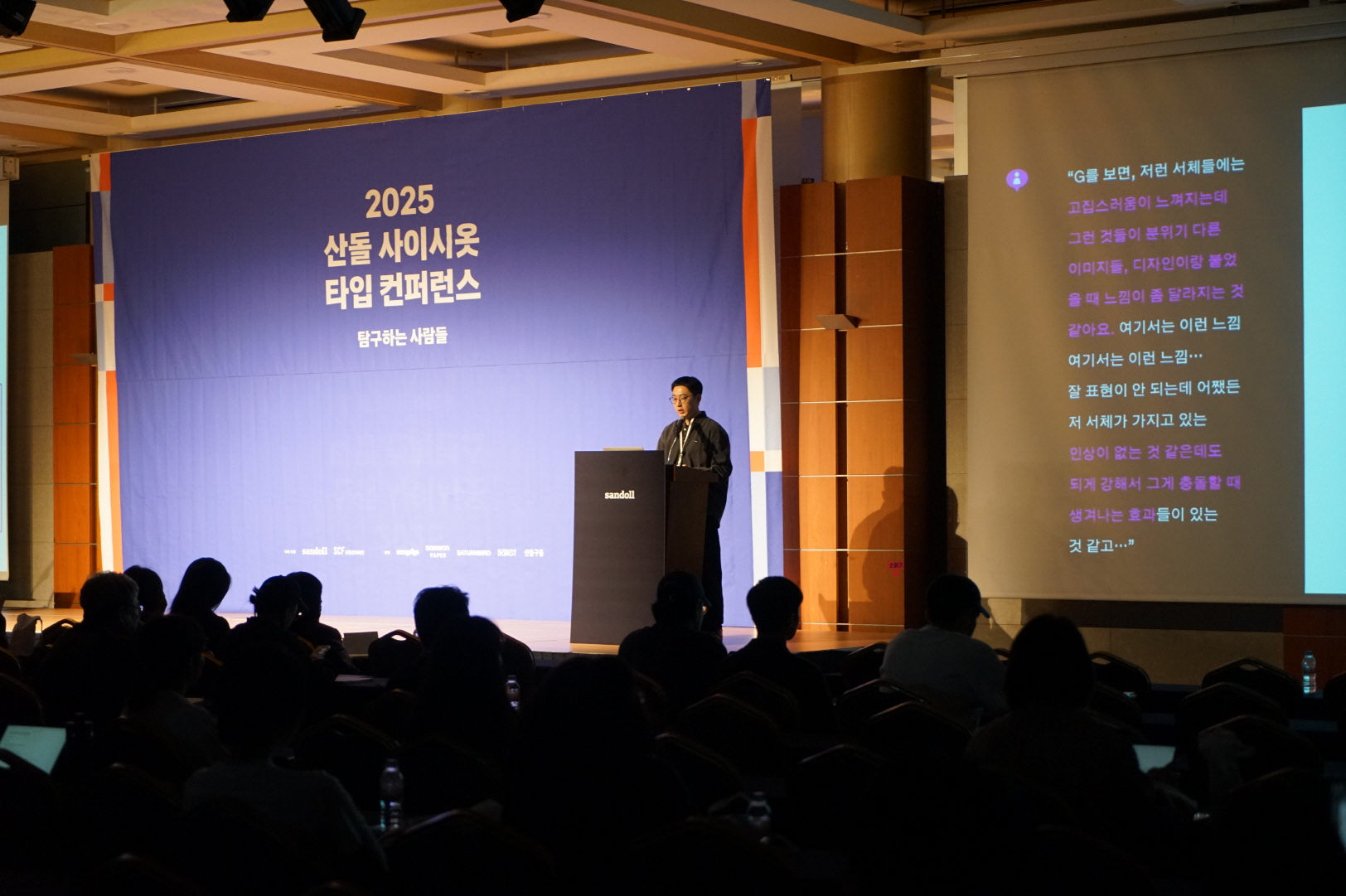
백범김구기념관 컨벤션홀에서 진행된 2025 산돌 사이시옷에 많은 청중이 모여 강연을 듣고 있다.
한글의 가치로 문화를 확산하는 재단법인 산돌문화재단(이사장 손연홍)이 주최하고 ㈜산돌(대표이사 윤영호)이 주관한 연례 폰트 컨퍼런스 ‘2025 산돌 사이시옷’이 지난 18일(토) 백범김구기념관 컨벤션홀에서 성황리에 막을 내렸다.
올해 사이시옷은 ‘탐구하는 사람들’을 주제로 열렸으며, 폰트 및 그래픽 디자이너, 엔지니어, 기획자, 예비 창업자, 관련 전공 학생 등 약 300여명이 참석해 폰트와 콘텐츠 산업의 현재와 미래를 함께 모색했다.
특히 이번 행사는 한글 폰트를 중심으로 K-컬처가 전 세계로 확산되는 과정에서 폰트가 감정과 정체성을 전하는 핵심 매개체로 부상하고 있음을 조명했다. 한글 활자의 조형적 아름다움과 디지털 기술, 그리고 브랜드 경험을 결합하며, 폰트가 K-콘텐츠를 구성하는 시각 언어의 기반으로 자리하고 있음을 확인했다.
컨퍼런스는 세 개의 세션으로 구성돼 각기 다른 시각에서 폰트와 디자인, 브랜드 경험을 다뤘다. 첫 번째 세션 ‘아침의 빛, 한글 원전 활자를 다시 비추다’에서는 황일선 민음사 미술부 북디자이너와 장가석 산돌 디자인스튜디오 타입디자이너가 전통 활자 복원을 통해 현대 감성에 맞게 재해석한 ‘SD초양’의 제작기를 공개했다. K-컬처에 대한 세계적 관심이 높아진 상황에서 옛 활자를 현대적으로 복원한 SD초양은 한글의 미학과 정체성을 새롭게 조명하며 청중의 높은 관심을 이끌었다.
두 발표자는 원전 자료를 기반으로 전통 활자의 조형적 아름다움을 현대적으로 되살린 과정과 디지털 시대에 한글 폰트가 가지는 문화적 의미를 설명하며 청중과의 즉문즉답을 통해 활발한 토론을 이어갔다.
이어 민본 서울여자대학교 교수는 ‘활자를 디자인한다구? – 복원과 재해석 사이, 보이지 않는 축 위의 활짝 명조’를 주제로 전통 활자의 복원과 현대적 해석 가능성을 심도 있게 탐구해 큰 호응을 얻었다.
두 번째 세션은 브랜드 경험 설계와 브랜딩 전략을 중심으로 진행됐다. 전우성 시싸이드 시티 대표는 삼성전자, 네이버, 29CM, 스타일쉐어 등에서의 실무 경험을 바탕으로 ‘핵심경험’을 주제로 강연하며 기업이 소비자와 감정적으로 연결되는 방식을 짚었다. 이어 송호성 호라이즌유니온 대표는 ‘통합적 사고가 만드는 훌륭한 경험의 설계’를 통해 디지털 시대에 브랜드가 일관된 사용자 경험을 구축하기 위한 전략적 접근을 제시했다.
마지막 세션에서는 현대 디자인 언어와 조형의 확장 가능성을 다뤘다. 전채리 CFC 대표는 ‘CFC의 탐구와 해석, 그리고 조형’ 강연을 통해 스튜디오 운영 경험과 디자인 철학을 공유하며 브랜드와 조형 언어의 관계를 풀어냈다. 이어 박이랑 현대백화점 브랜드전략팀장은 ‘현대다운 언어’를 주제로 리테일 브랜드 전략 속 폰트의 중요성을 짚으며 발표를 마쳤다.
행사 종료 후 진행된 청중 만족도 조사 결과 97.5% 이상이 내년도 행사 재참여 의사를 밝혔다. 또한 현장에서는 “폰트가 감정과 정체성을 표현하는 핵심 언어로서 글로벌 시장에서 K-콘텐츠의 영향력이 커지는 흐름을 이해하는 데 큰 도움이 됐다”, “한글 활자의 전통과 현대가 자연스럽게 맞닿는 지점을 생생하게 느낄 수 있었다” 등 긍정적인 반응이 이어졌다.
산돌문화재단 관계자는 “사이시옷은 폰트를 통해 문화와 산업, 그리고 대중이 연결되는 장으로 발전하고 있다”며, “K-컬쳐가 세계적으로 확산되는 지금, 한글 폰트는 그 감성과 철학을 가장 순수한 형태로 전달하는 언어이자 기술이다. 앞으로도 폰트를 기반으로 한 K-콘텐츠 생태계 확산을 위해 다양한 교육, 전시, 학술 프로그램을 이어가겠다”고 밝혔다.
이번 ‘2025 산돌 사이시옷’은 전통 활자에서 현대 브랜딩, 그리고 조형 언어로 이어지는 폭넓은 탐구의 장으로, 폰트가 K-콘텐츠 시대의 핵심 경쟁력으로 자리 잡고 있음을 확인한 행사로 평가받았다.